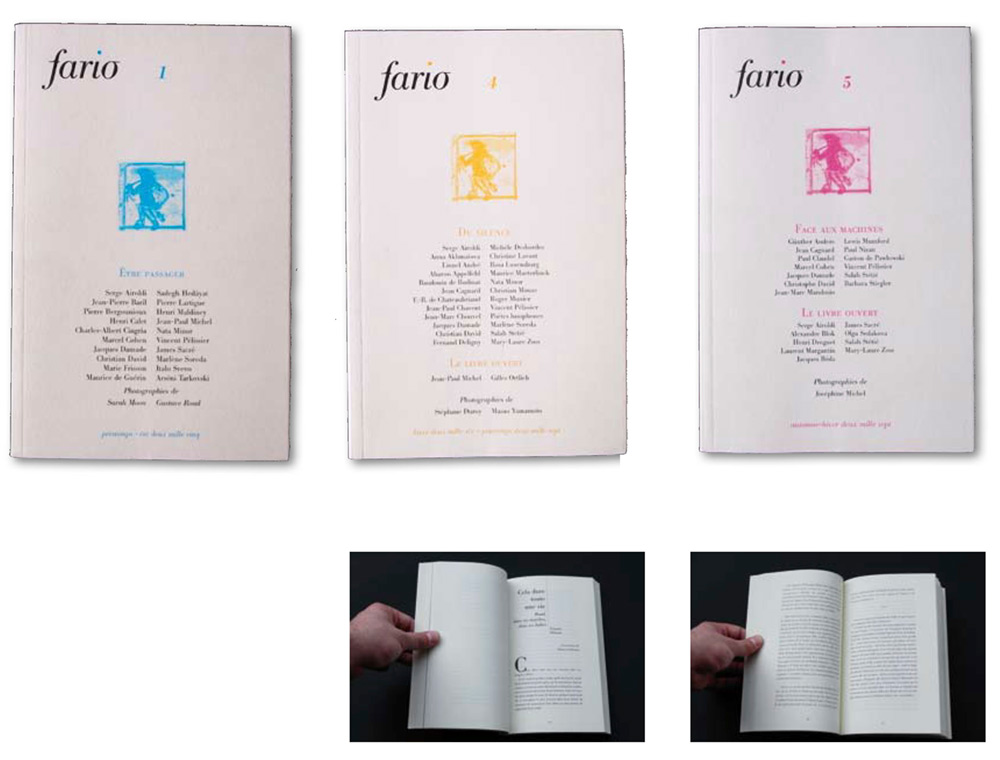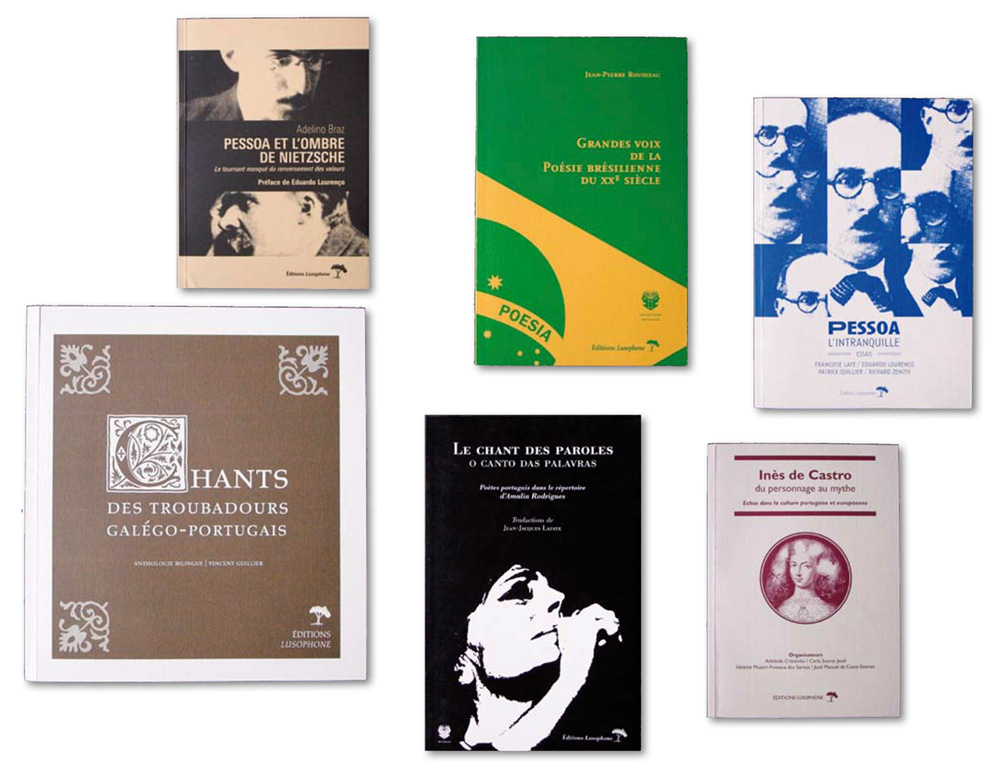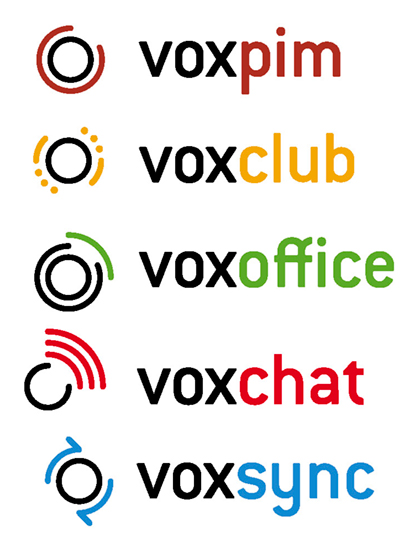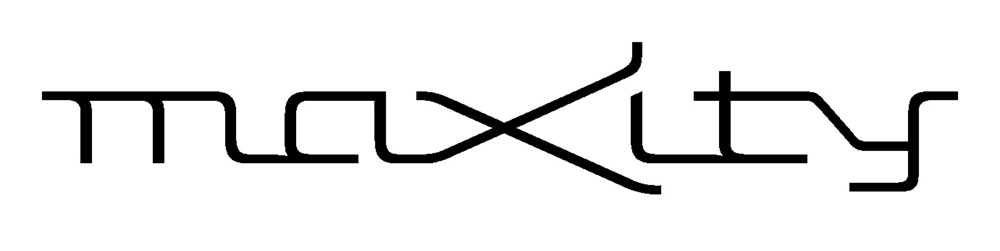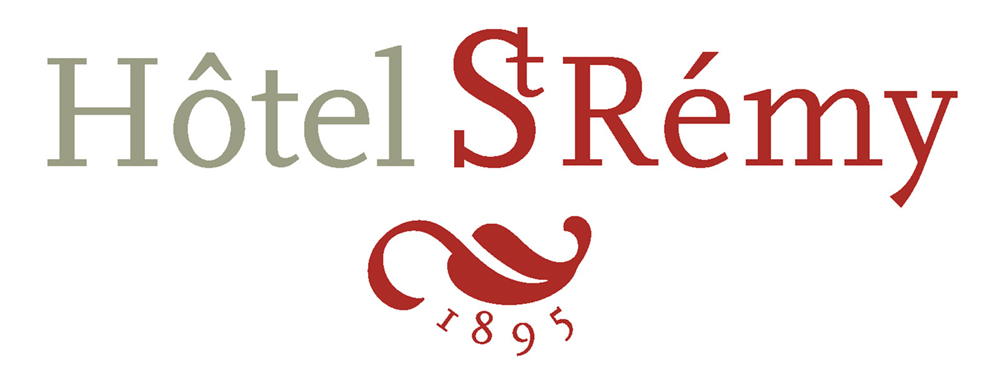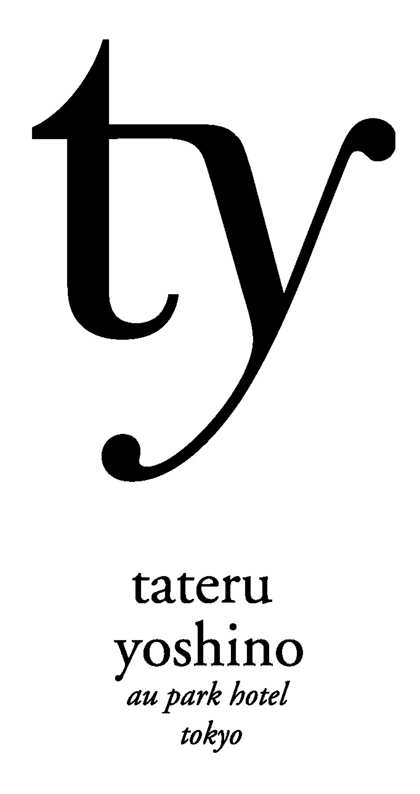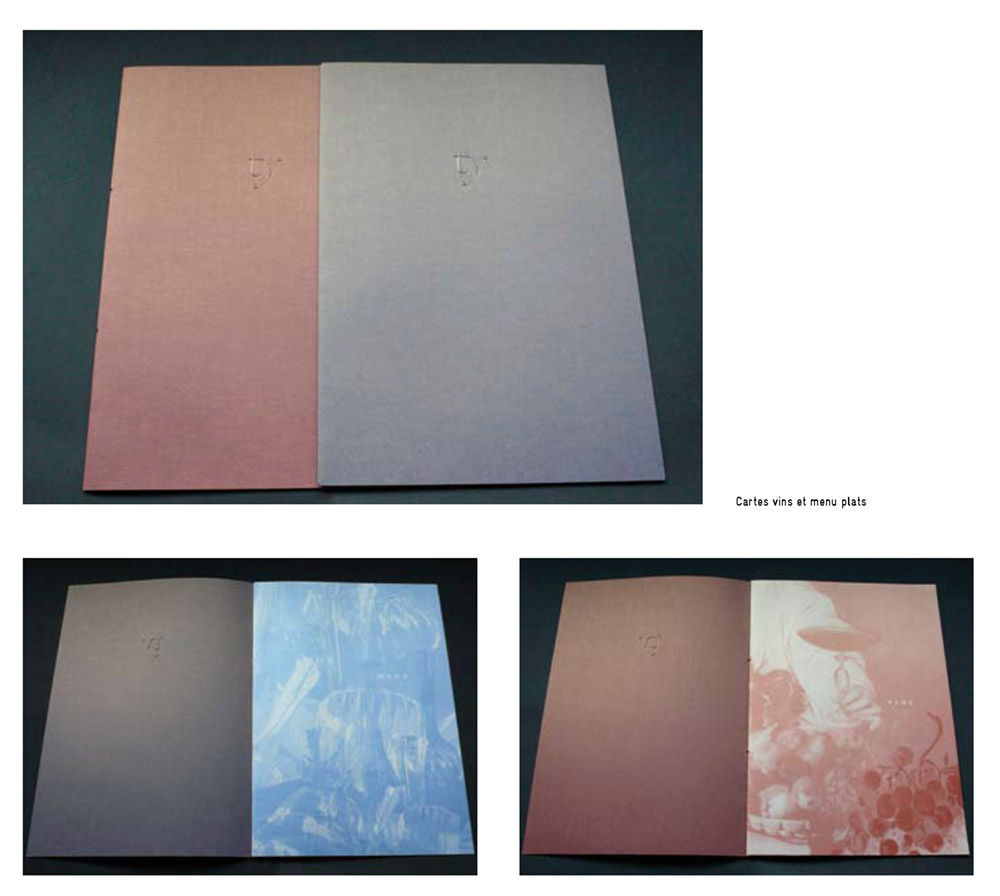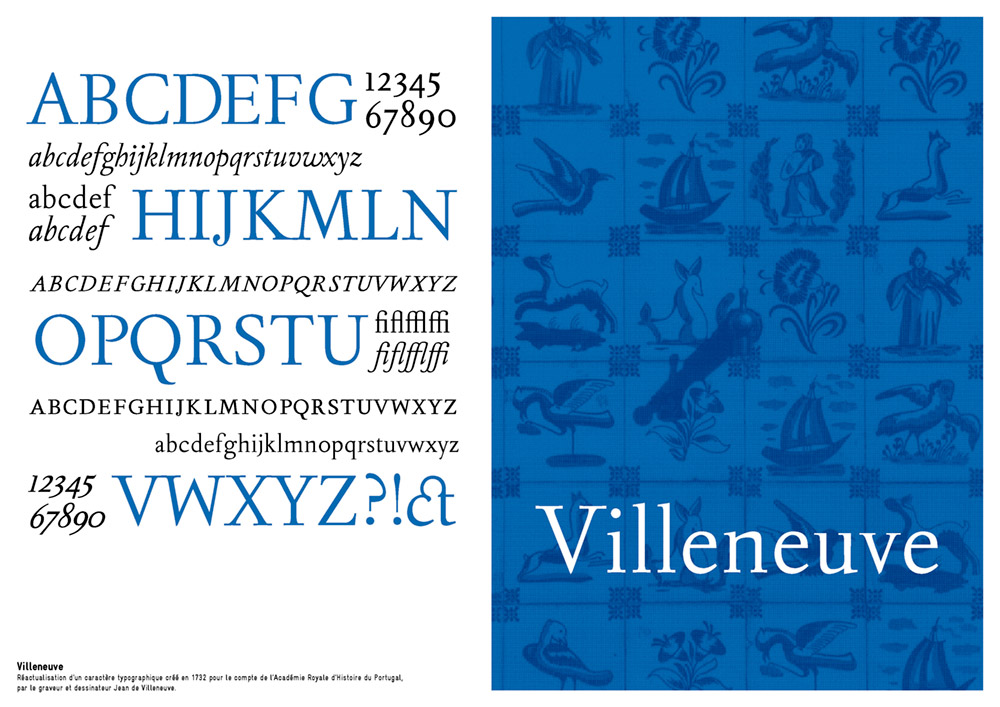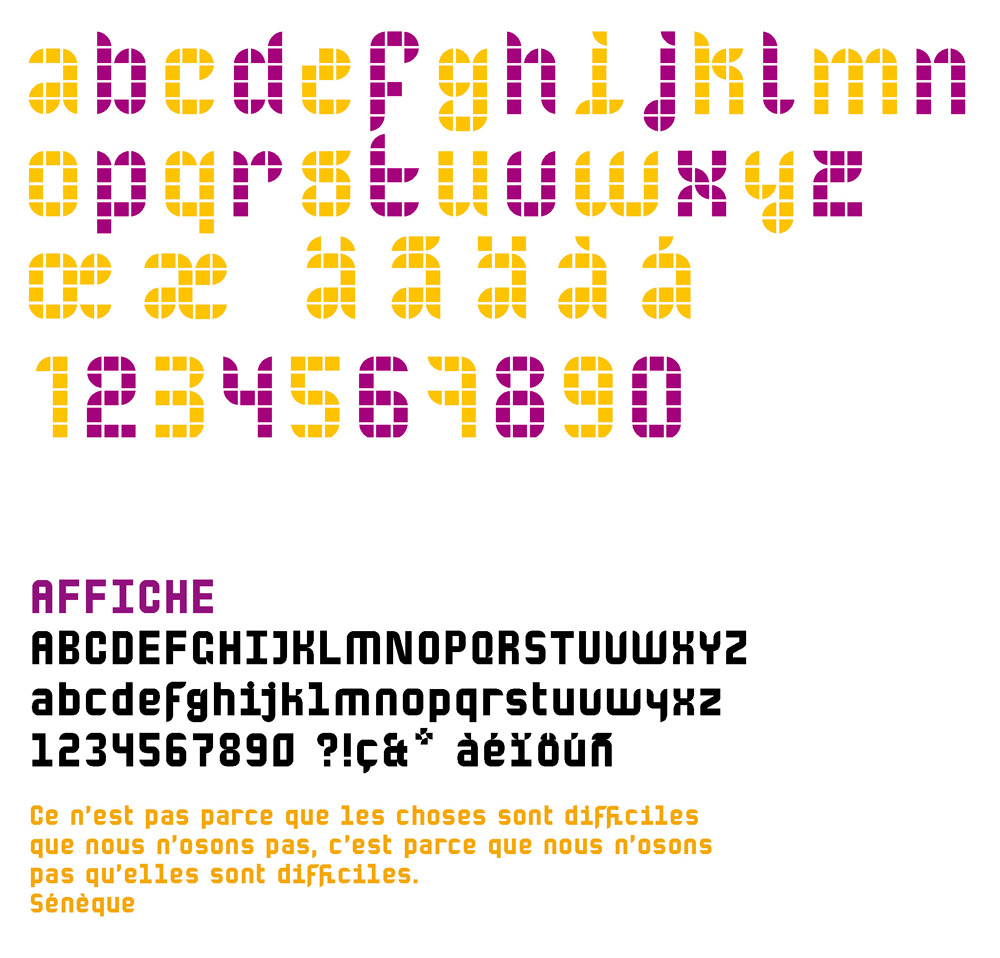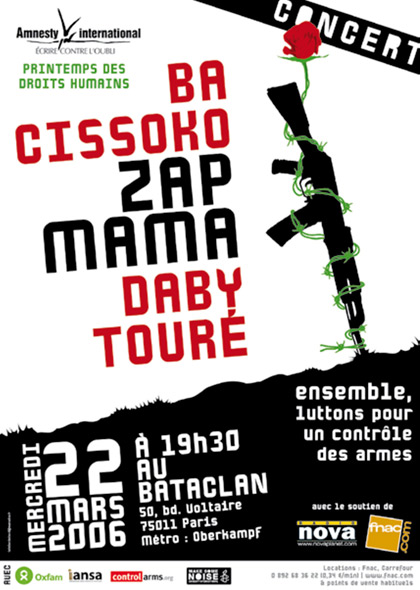
David Laranjeira enseigne la typographie à e-artsup
Pas mal de changements dans l’enseignement d’e-artsup (site en reconstruction), pressenti d’abord Christophe Badani, puis Jean-Baptiste Levée. Tous les deux pris dans l’enfer de l’enseignement à l’Académie Charpentier, ils me recommandèrent finalement David Laranjeira, un outsider de grand talent. David, comme vous pouvez le constater a une carrière assez courte pour l’instant, mais sa formation, son goût pour l’expérimentation, la variété de ses travaux à la fois graphiques et typographiques lui donnent toute légitimité à entraîner les étudiants sur les territoires de la lettre et de sa composition. Vous détaillerai son programme pédagogique au fil des billets de D&T.
Fario revue littéraire semestrielle
Fario
Conception et réalisation de l’ouvrage (intérieur et couverture)
Éditions Lusophone
Conception et réalisation graphique (Anthologies poétiques bilingues, études, récits, essais…)
Éditeur de logiciel
Voxmobili
Conception et finalisation du logotype fédérateur et des déclinaisons produits
Régie publicitaire de l’OpenTour
Maxity (via ID Source)
Finalisation typographique
Hotel-Restaurant, à Ferrières (77)
Groupe Accelis (via ID Source)
Conception et finalisation
Restaurant de gastronomie française, à Tokyo (Japon)
Tateru Yoshino (via Dé Signe)
Conception et finalisation. Déclinaison sur support cartes de menus.
Organisateur d’excursions
Cityrama (via ID Source)
Conception et finalisation
Hotel, à Tokyo (Japon)
Park Hotel, Tokyo (via Dé Signe)
Choix typographique en accord avec le visuel existant.
Fabricant de matériel orthopédique japonais
Dr. Comfort (via Dé Signe)
Conception et finalisation
Villeneuve
Réactualisation d’un caractère typographique créé en 1732 pour le compte de l’Académie Royale d’Histoire du Portugal,
par le graveur et dessinateur Jean de Villeneuve.
Recherche typographique et déclinaison sous la forme du caractère «Affiche»
Caratère développé pour une affiche réalisée pour le compte de la section jeunes d’Amnesty France.
Zink
Police de caractère construite sur une base de 9 cases, et allant d’une version lisible à une version censée ne contenir
qu’un minimum d’information pour chaque caractère.
Distribuée par la fonderie numérique T26
L’Estranger (exercice de style)
Déclinaison en police de caractère complète du logotitre d’une revue de bandes-dessinées
Recherche
Dégager tous les caractères de l’alphabet en retirant le minimum de matière à un carré
Recherche
À partir d’un jeu de formes donné au départ, créer le maximum de variantes possibles pour chaque caractère (en développement)
Recherche
D’après Albers, recherche de caractère pour une affiche en faveur de la libération de prisonniers politiques